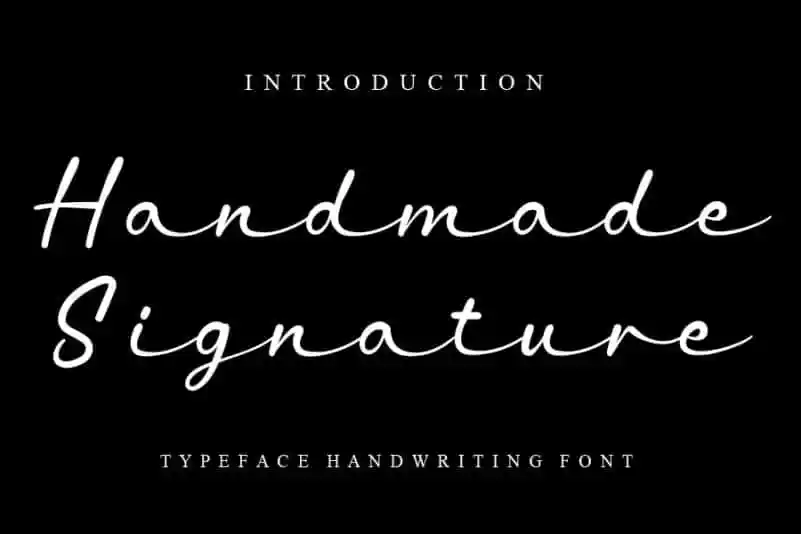
Handmade Signature Script Font – Fonte Grátis
Handmade Signature Script Font
Esta fonte ‘Handmade Signature Script Font’ é perfeita para quem busca uma experiência autêntica e única no design de seu documento. Inspirada na arte natural do traçado de nomes, essa fonte oferece um toque pessoal que pode tornar seu trabalho realmente especial. Feita especialmente por CreativeLetter, esta fonte adquire um caráter ímparcialmente autêntico, com linhas suaves e texturas naturais. Ela é perfeita para anotações de gravação, resumos, cartas pessoais ou até mesmo trabalhos publicitários que buscam uma conexão mais profunda com seu destinatário. Com um design cuidadosamente elaborado por um designer talentoso, a ‘Handmade Signature Script Font’ é ideal tanto para aqueles buscando um estilo elegante e sofisticado quanto para quem deseja criar uma atmosfera descontraída e criativa. Em um mundo cada vez mais digital, esta fonte oferece uma maneira verdadeiramente personalizada de destacar seu trabalho.